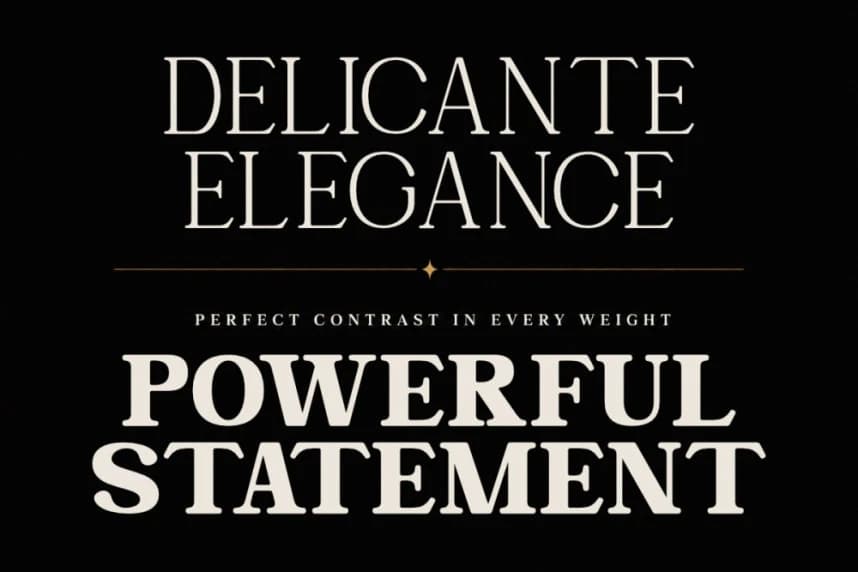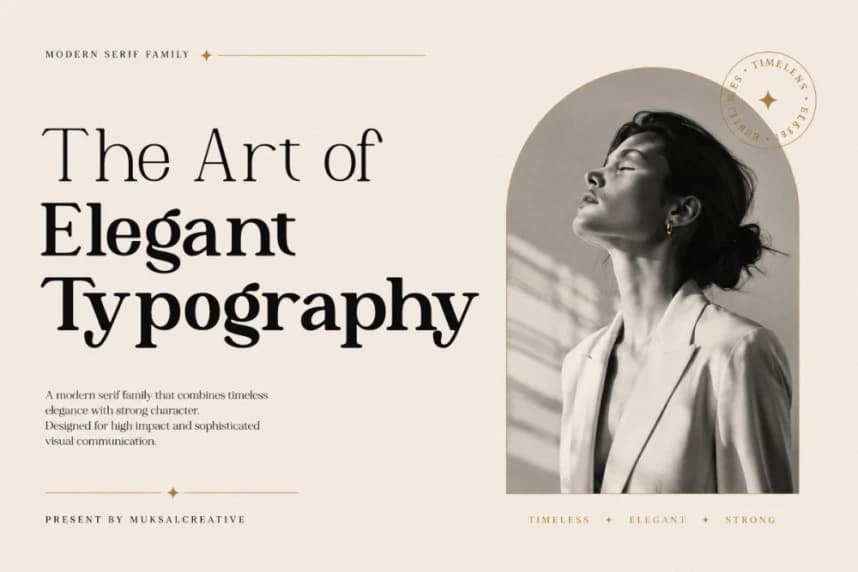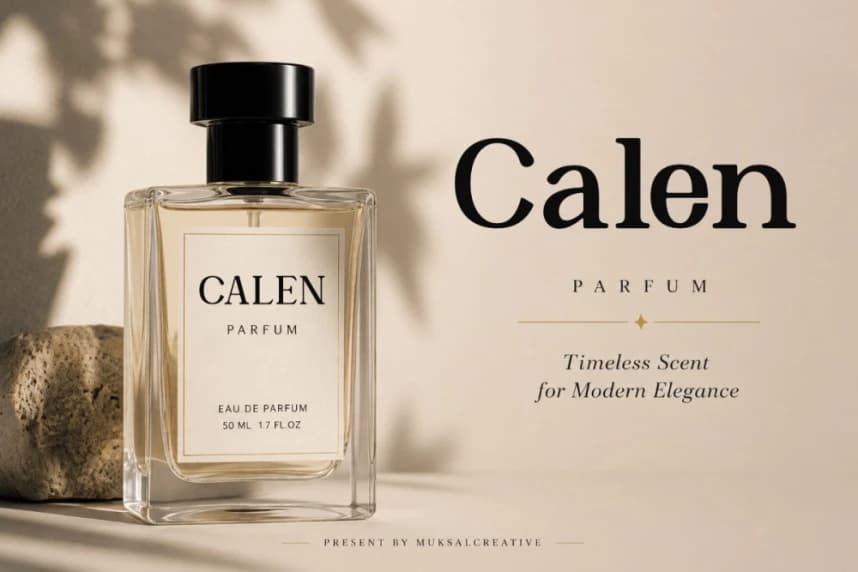
Sendra Font
Sendra Font, zamansız zarafet ve güçlü görsel karakteri tek sofistike bir tip sistemi içinde sunmak amacıyla tasarlanmış zarif bir modern serif ailesidir. Lüks editoryal çalışmalardan, üst düzey marka kimliğinden ve çağdaş moda tipografisinden ilham almıştır.
Sendra Font, zamansız zarafeti ve güçlü görsel karakteri tek sofistike bir tip sistemine kazandırmak üzere tasarlanmış rafine bir modern serif ailesidir. Lüks editoryal çalışmalardan, üst düzey marka kimliğinden ve çağdaş moda tipografisinden ilham almıştır.